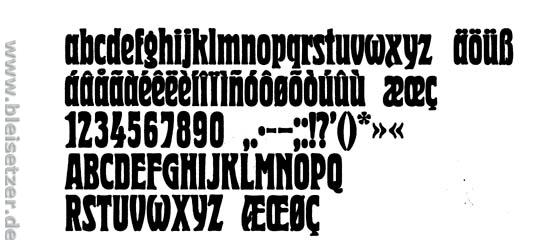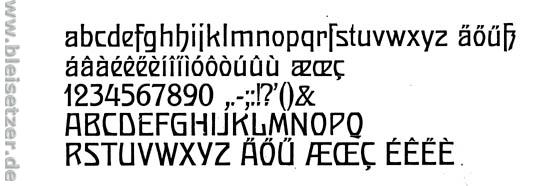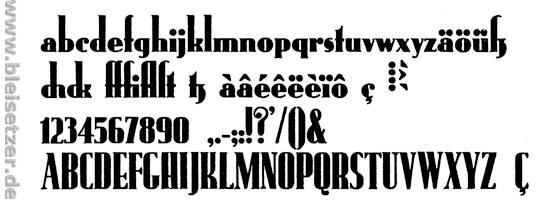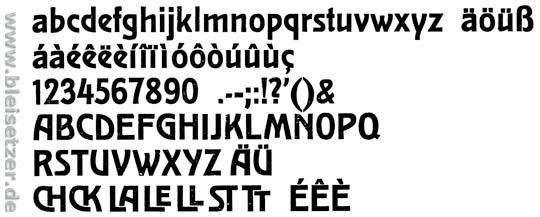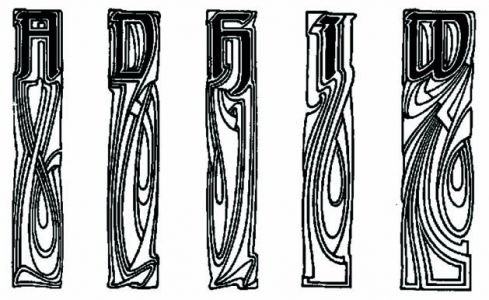
jugendstil und arts&crafts schriften gesucht
ich suche die namen folgender schriftarten
und eigentlich suche ich noch namentlich einige weitere schriftarten, die der jugendstil und die arts&crafts bewegung hervorgebracht haben ... jemand einen einfall? :D
Dein erstes Beispiel sind die Initialen der Behrensschrift, von Peter Behrens und die Ruhard'sche/Gebr. Klingspor Schriftgießerei. Davon exitiest keine echte digitale Version, leider. Es kann sein, dass du ein "Qucik & Dirty" Free Font Digitalisation irgendwo finden könntest…
Arts & Crafts –
Das ist die
Herold Reklameschrift
H.Berthold AG, Berlin
Erstguß 1904
Hermann Hoffmann
Andreas Seidel hat sie digitalisiert:
Das hier ist die
Lang-SchriftDreslersche Gießerei F.Flinsch
Erstguß 1905
Paul Lang
Das ist die
Rundfunk
H.Berthold AG, Berlin
Erstguß 1928
Entwurf Adolf Behrmann
Ich meine, die gäbe es auch digitalisiert.
Und dies ist die
Skulptur, HalbfetteEmil Gursch, Berlin
Erstguß ca. 1900
Hausschnitt
Dein erstes Beispiel sind die Initialen der Behrensschrift, von Peter Behrens und die Ruhard'sche/Gebr. Klingspor Schriftgießerei. Davon exitiest keine echte digitale Version, leider. Es kann sein, dass du ein "Qucik & Dirty" Free Font Digitalisation irgendwo finden könntest…
Diese Behrens-Initialen sind so schön..
man könnte weinen.
Jetzt hatte ich auch Zeit, den Link zur digitalisierten Form der Herald-Reklame von Andreas Seidel herauszusuchen. Es ist eine Variation der Herald und heißt Heraut:
Andreas Einverständnis voraussetzend, hier sein Kommentar zu meiner damaligen Rückfrage, warum er sie „Heraut“ genannt hat:
„Herold wird als Schriftname schon von den Hunts ("Berthold" Chicago) und Paratype (Russland) benutzt und war deshalb nicht mehr verfügbar. Heraut basiert aber auf dem selben Design von Heinz Hoffmann. Es gab diese Schrift in unterschiedlichen Ausführungen und der Stil wurde von anderen Gießereien schon damals adaptiert.“
Ich meine, seine Heraut ist sehr schön gelungen.
Die berühmte Eckmann-Schrift aus dem Jahre 1900 ist im Internet als "Rudelsberg" kostenlos herunterladbar. Im Gegensatz zur kostenpflichtigen derzeit online erhältlichen "Eckmann" hält sich die "Rudelsberg" exakt an Otto Eckmanns Schriftentwurf. Herr Steffmann hat noch andere historische Schriften auf seiner Website.
Und dies ist die
Skulptur, HalbfetteEmil Gursch, Berlin
Erstguß ca. 1900
Hausschnitt
Gibt es die Skulptur auch in digitaler Form?